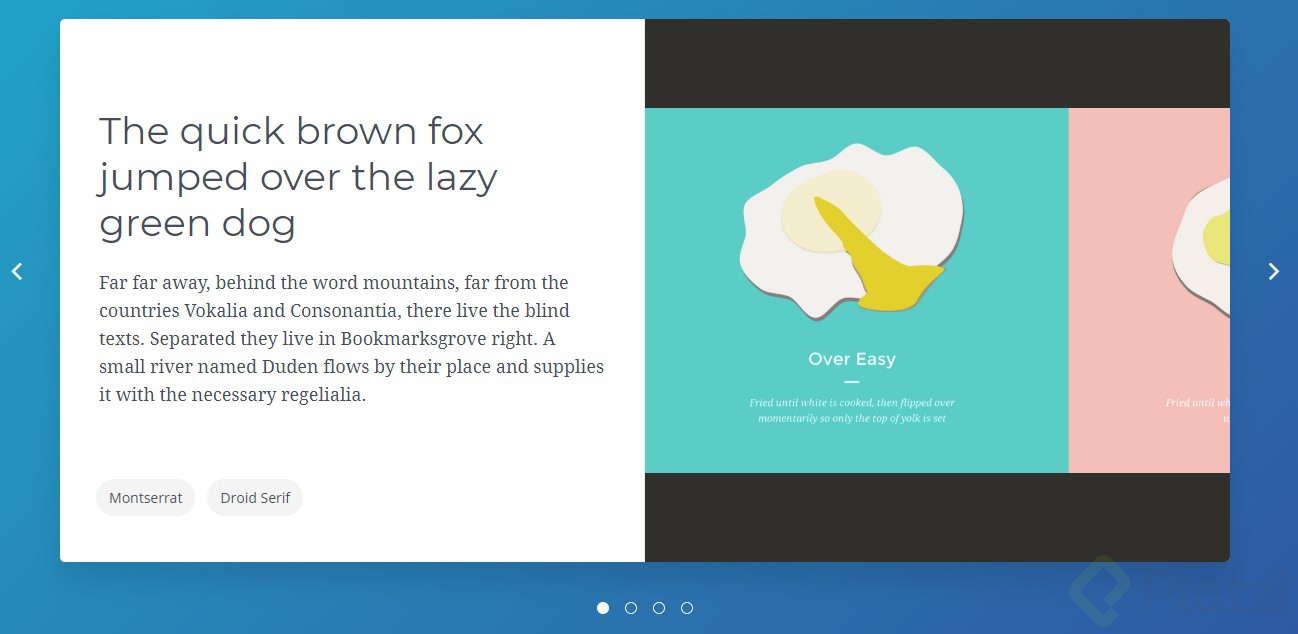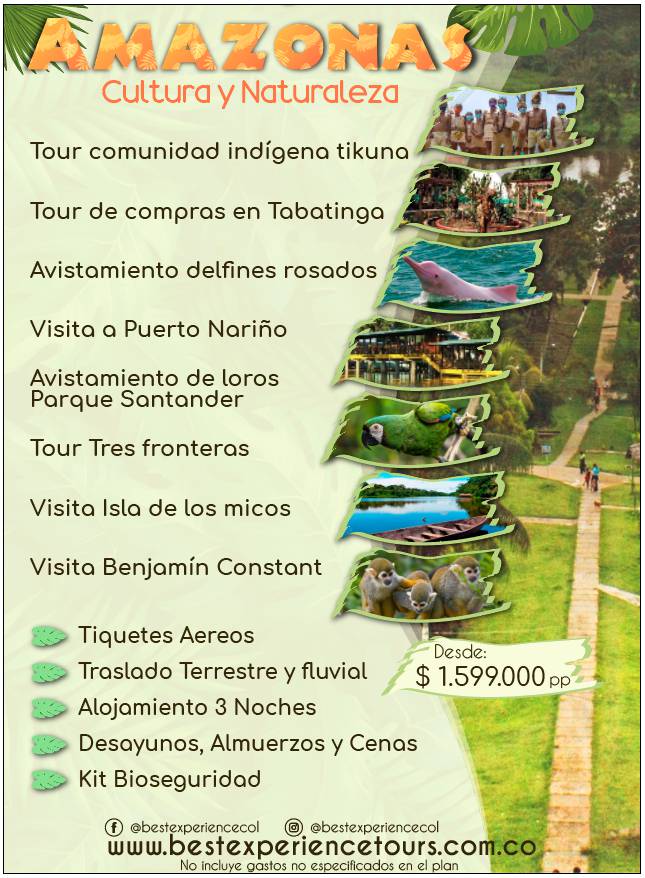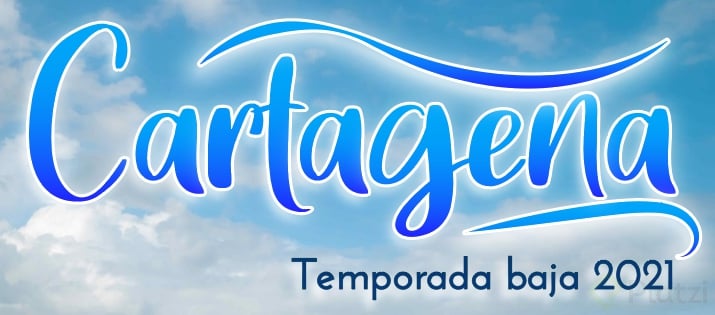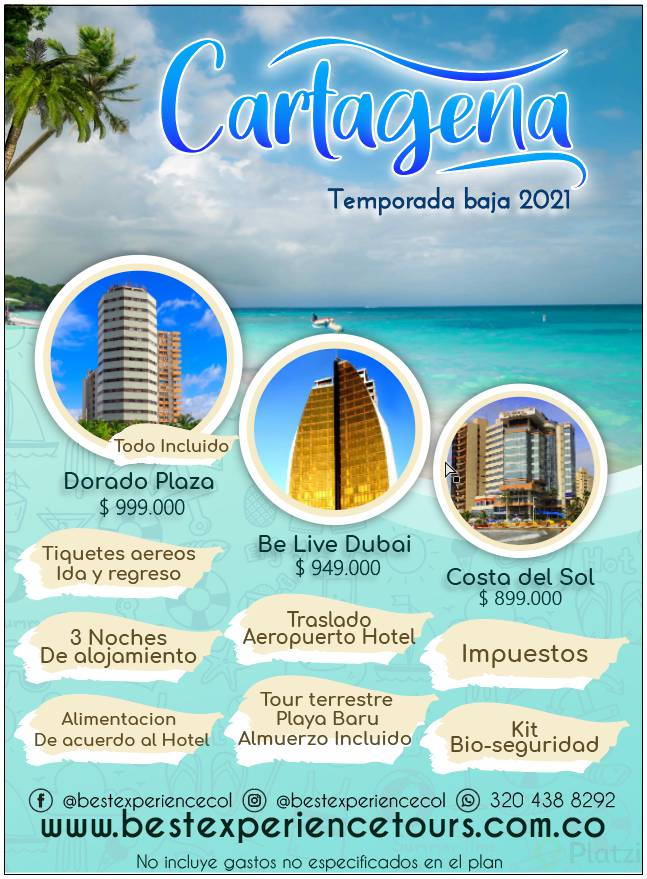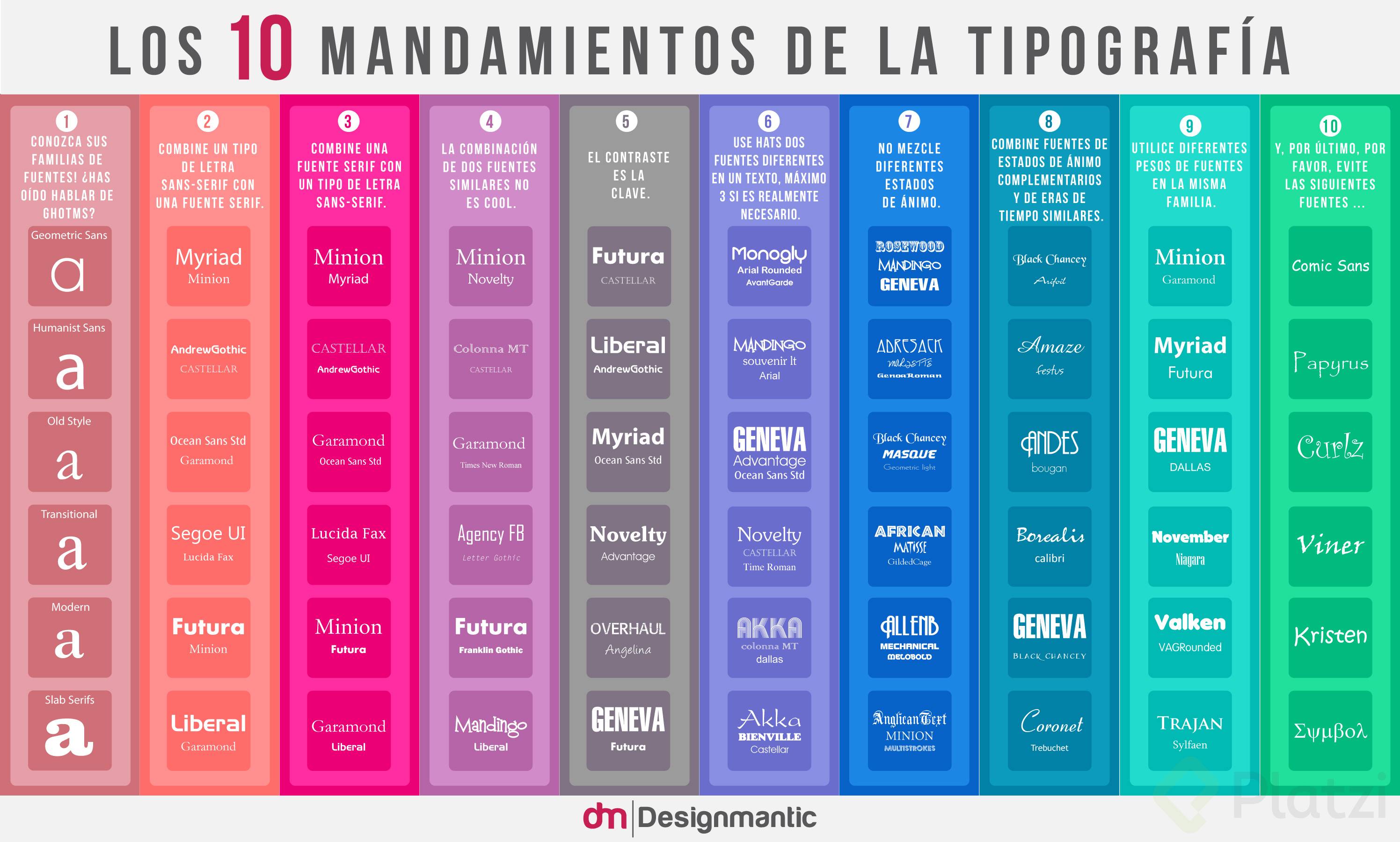
Si la tipografia asi lo permite, ¿está bien visto que dentro de un documento en una sección se utilice una Sans para titulos y una Serif para cuerpo y en otra sección se invierta el orden(la serif para titulo y la sans para cuerpo? ¿O no es una buena practica?
ProfesorEs una opción. Funcionaría si la temáticas cambia y necesitas hacer una diferenciación de contenidos.
Les comparto una pequeña recopilación de combinaciones tipográficas espero sea de utilidad
¿Por qué es mejor buscar armonía estructural?
Buscar la armonía estructural es fundamental porque crea un hilo conductor invisible entre dos fuentes que, a simple vista, parecen muy distintas. Cuando combinas una tipografía con serifa y otra sin serifa, el riesgo de generar ruido visual es alto. Sin embargo, si ambas comparten el mismo esqueleto o eje de composición, el cerebro las percibe como un conjunto unificado.
Piensa en esto como dos personas de una misma familia vistiendo ropa de estilos completamente opuestos: aunque sus atuendos (las serifas o la ausencia de ellas) contrasten, sus rasgos faciales (la estructura de las letras) revelan su parentesco. Al elegir fuentes diseñadas bajo proporciones similares, logras que el diseño editorial se sienta cohesivo y profesional. Las letras se complementan de manera natural, permitiendo que el lector fluya por el texto sin distracciones ni choques visuales abruptos.
puedo utilizar para las redes sociales o solo sirve para edición editorial ?
Claro que sirve, todo este conocimiento es muy util en todo lo que tenga que ver con Tipografías.
Pero algo que debes tomar en cuenta y adaptar es el hecho de que para Redes Sociales el contenido se vera a través de un monitor o de una pantalla de celular y para eso hay que ver que tipo de fuentes son mas adecuadas para esos medios, que sean fáciles de leer y que no cansen la vista.
La clave es el contraste.
eN ALGUN MOENTO UTILICE ESTE CONTRASTE DE FUENTES, Sans con otras mas Script
pues yo siento que funciono y era para unos flyer, miren cuentenme ustedes porfa: